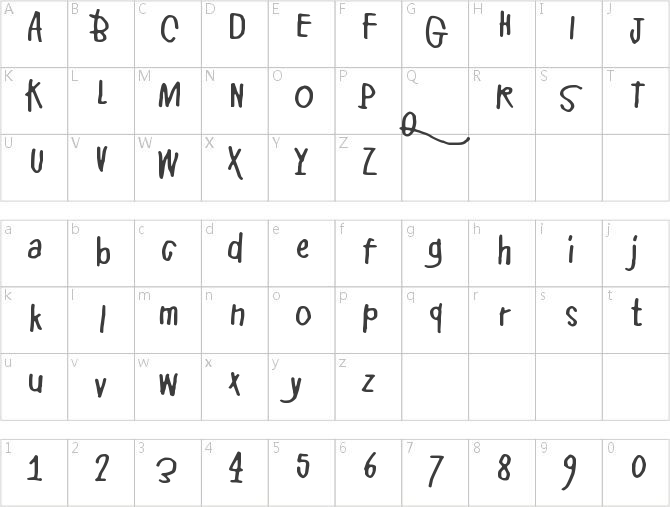
Pikku Julmuri 詳情頁(yè)
Pikku Julmuri字體字庫(kù)是一款讓人賞心悅目、百看不厭的英文字體,適合各類(lèi)廣告和產(chǎn)品包裝設(shè)計(jì)應(yīng)用,字體大小0.05MB,格式為ttf字體,上傳用戶(hù)是Apple,作者/版權(quán)方為未知